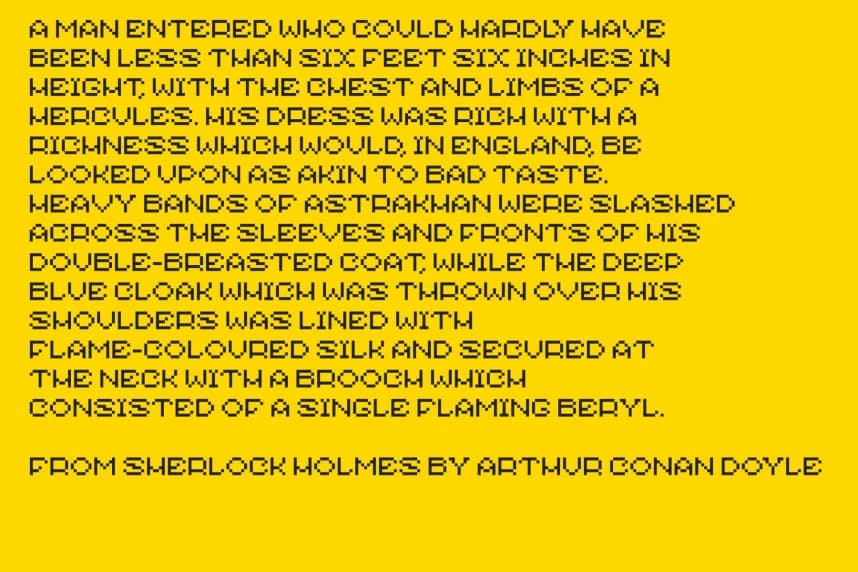
Pixeljo Font
PIXELJO Font, retro oyun estetiğini temiz bir çağdaş stil ile harmanlayan modern bir piksel gösterim yazı tipidir. Yapısal bir piksel ızgarası üzerinde kurulu olan bu yazı tipi, 8-bit nostaljik bir atmosfer sunarken güçlü okunabilirlik ve şık minimalist bir görünüm sağlar.
PIXELJO Font, retro oyun estetiğini temiz bir çağdaş stile harmanlayan modern bir piksel görüntü yazı tipidir. Yapılandırılmış bir piksel ızgarası üzerinde kurulu olan bu yazı tipi, güçlü okunabilirliği korurken nostaljik bir 8-bit atmosfer ve şık minimalist bir görünüm sunar.